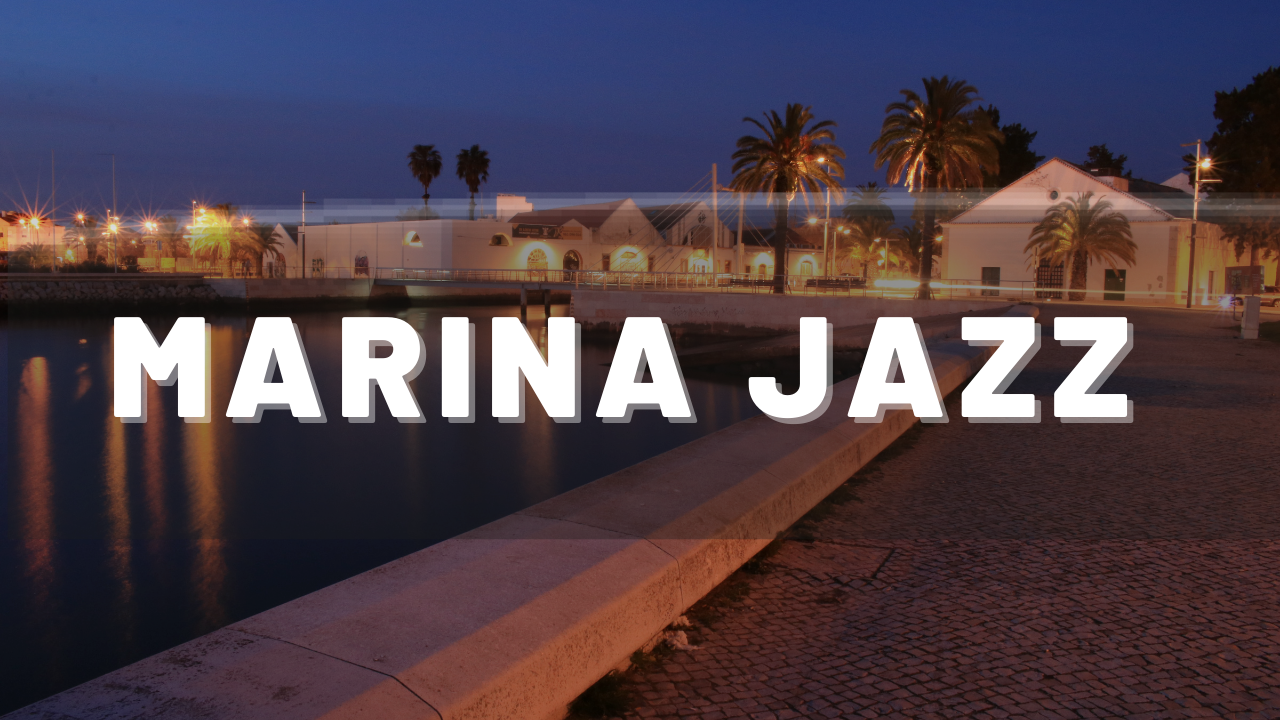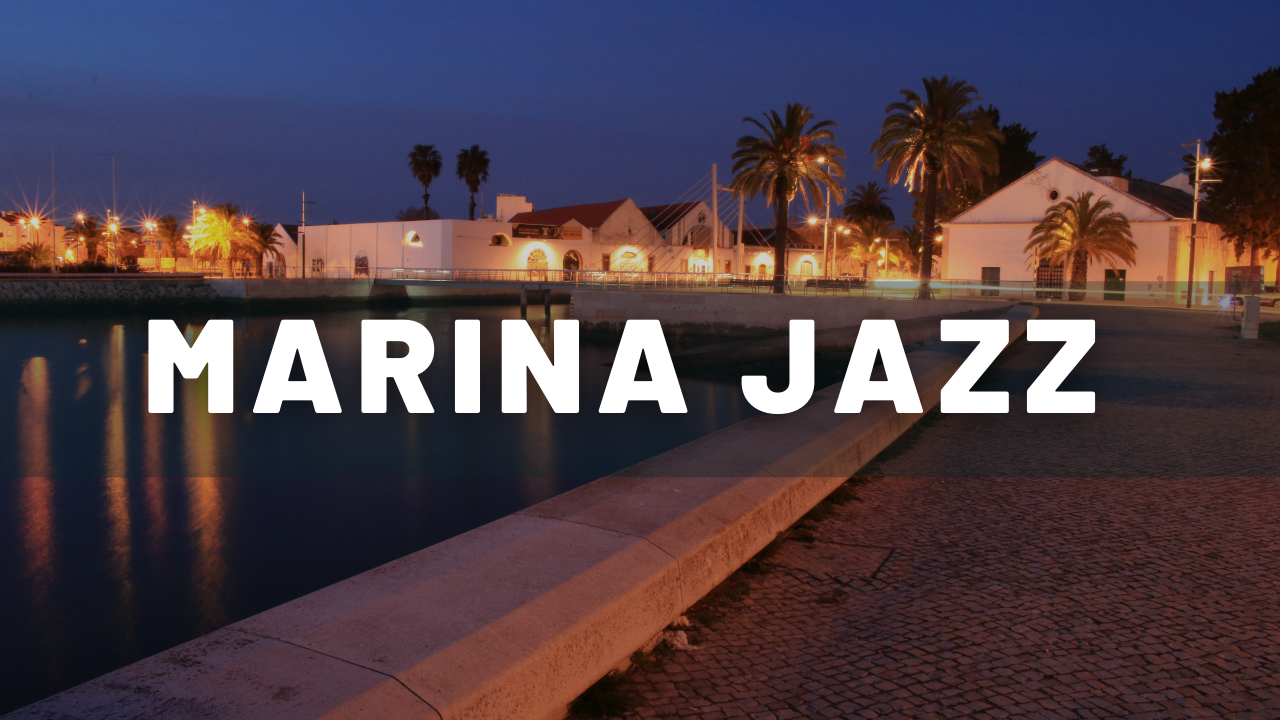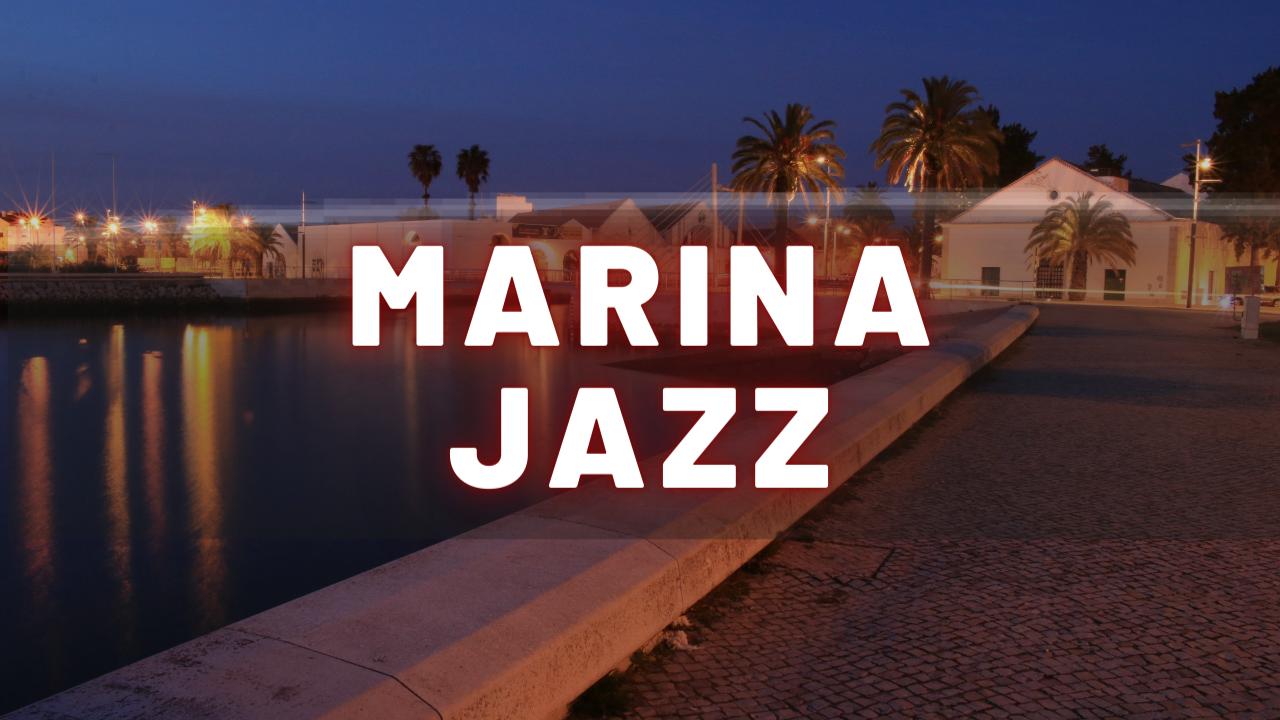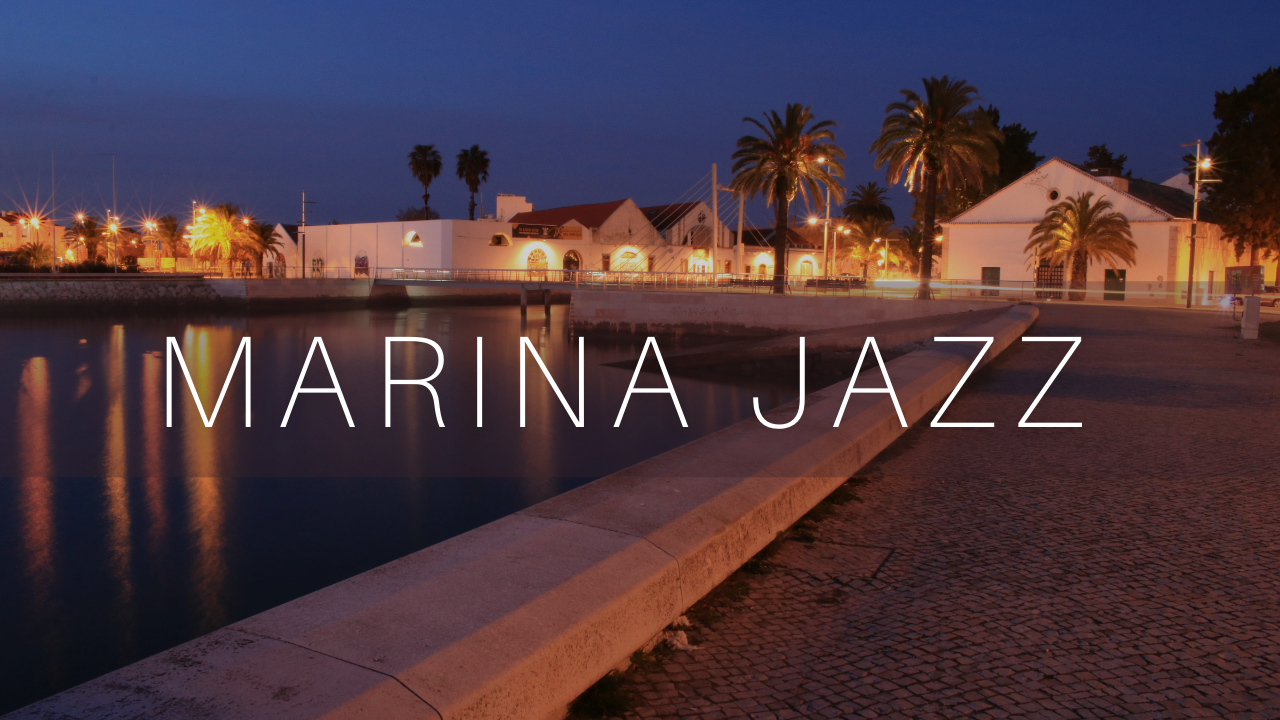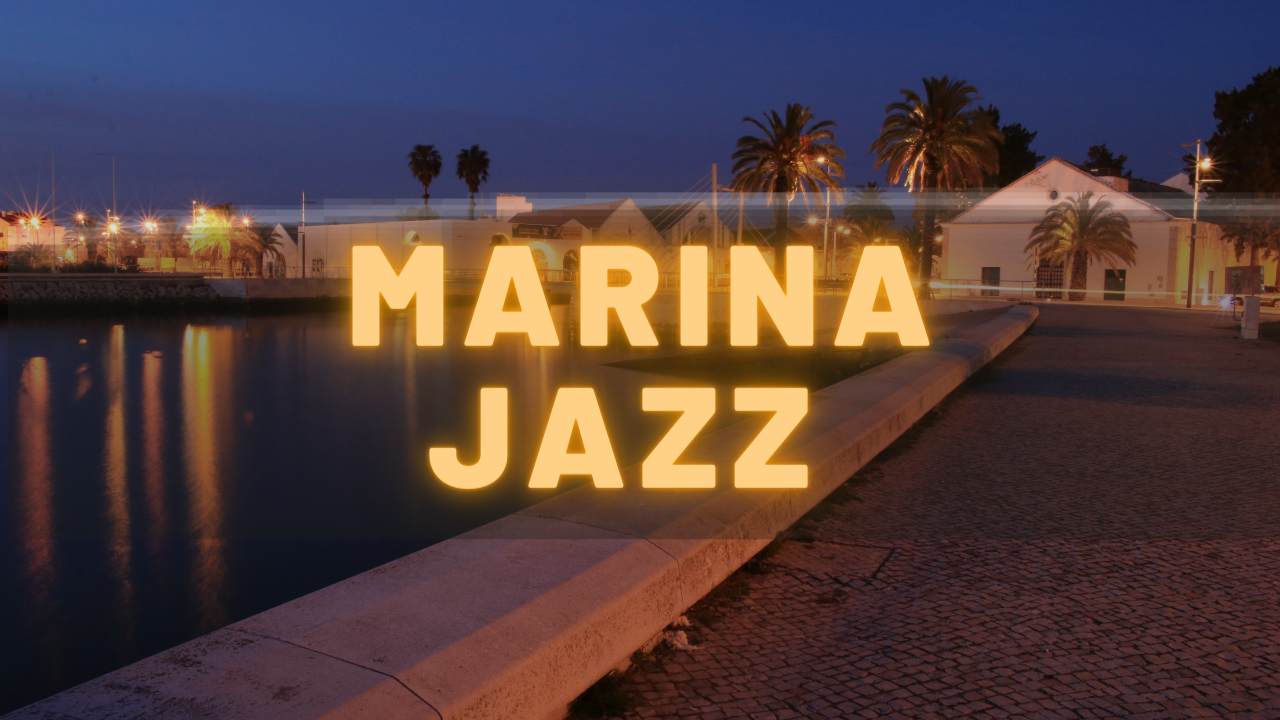
Seçin Hangisi? Font
Chill müzik ürettiğim bir youtube kanalım var. Sade , minimalist ve rahatlatıcı olması sebebiyle bir font üzerinde karar veremedim. Rakip kanal 1. resimdeki fontu kullanıyor. Bende birinciyi kullanıyorum
Ama hangisi daha Bu konsepti yansıtır?
Rakip Kanal Fontu ------
1. Gayet şık görünüyor
1. benim seçimim
2..
1. bence.